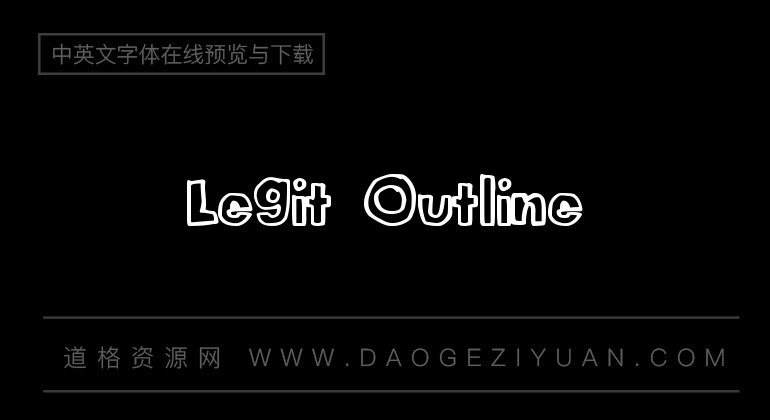
Legit Outline
Legit Outline 字体是一款细腻的轮廓字体,它的特点是字体的轮廓线条细腻,让字体看起来更加精致、细腻。Legit Outline 字体适用于标题、插图等,可以给文字增添更多的细节,使文字看起来更加有趣。此外,Legit Outline 字体也可以用于网页设计,可以给网页增加更多的细节,使网页看起来更加精致。
Legit Outline是一款非常不错的手写艺术字体,具有很好的视觉感,适合于文化类的宣传设计、商业类品牌的广告和产品包装设计以及个性化文字排版等较多场景。